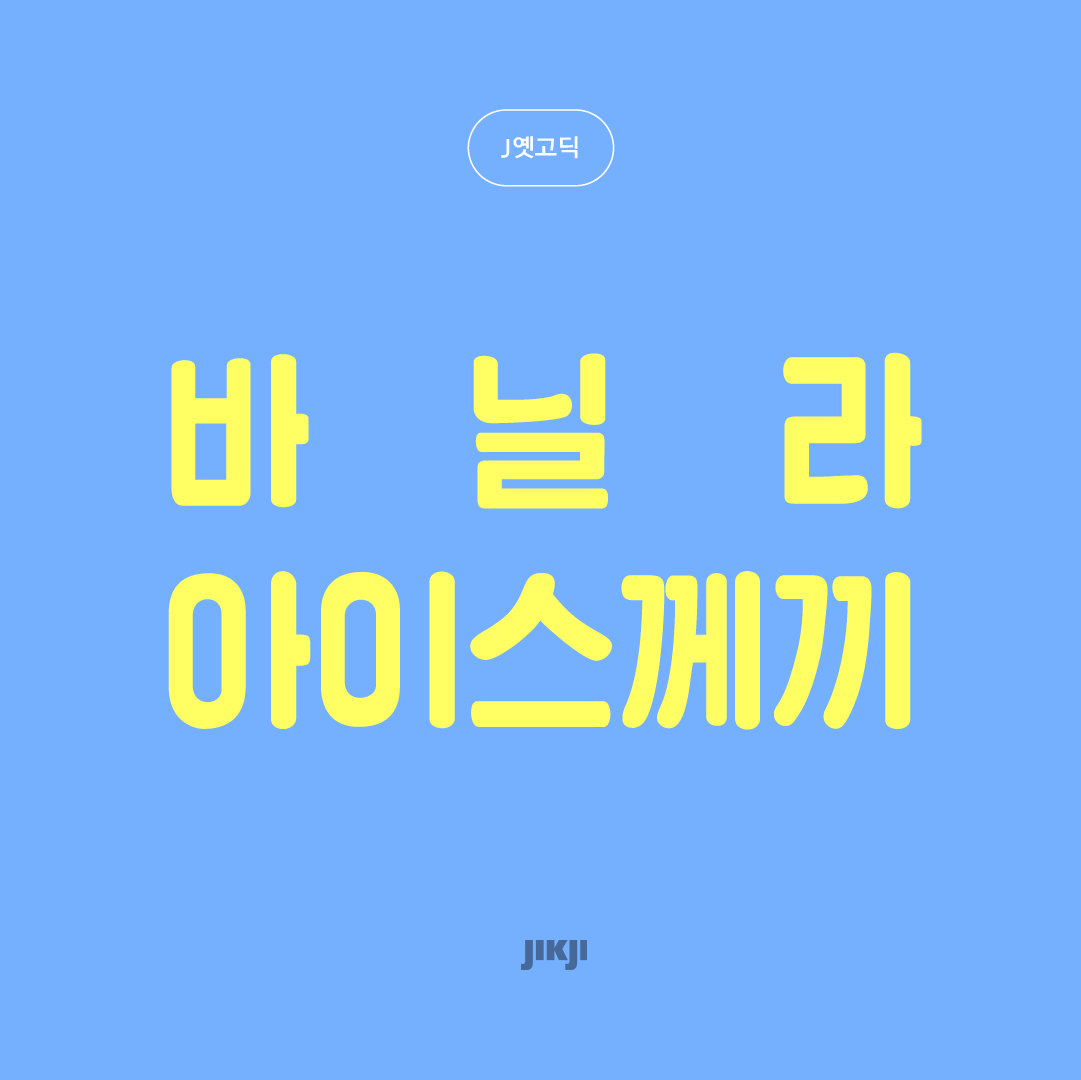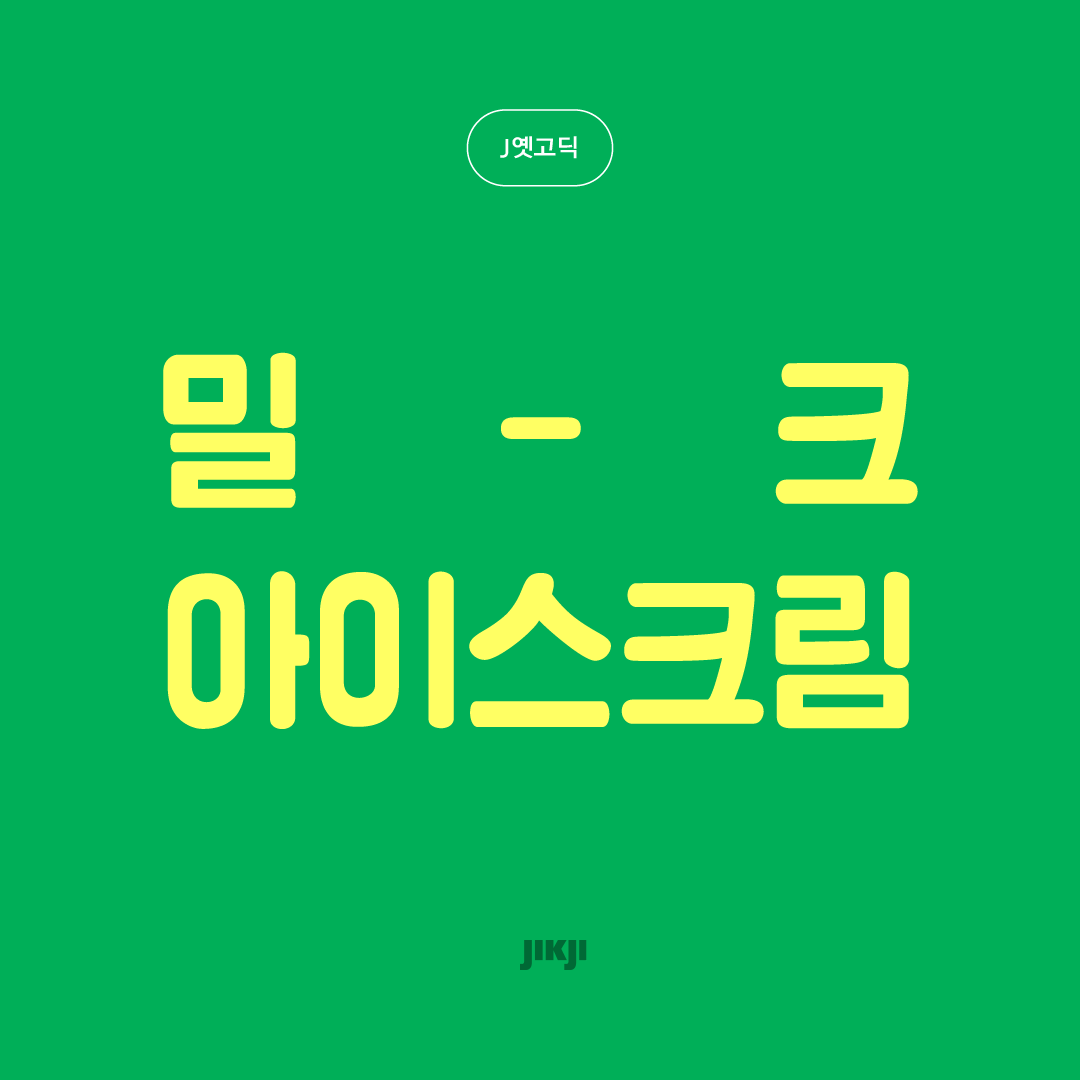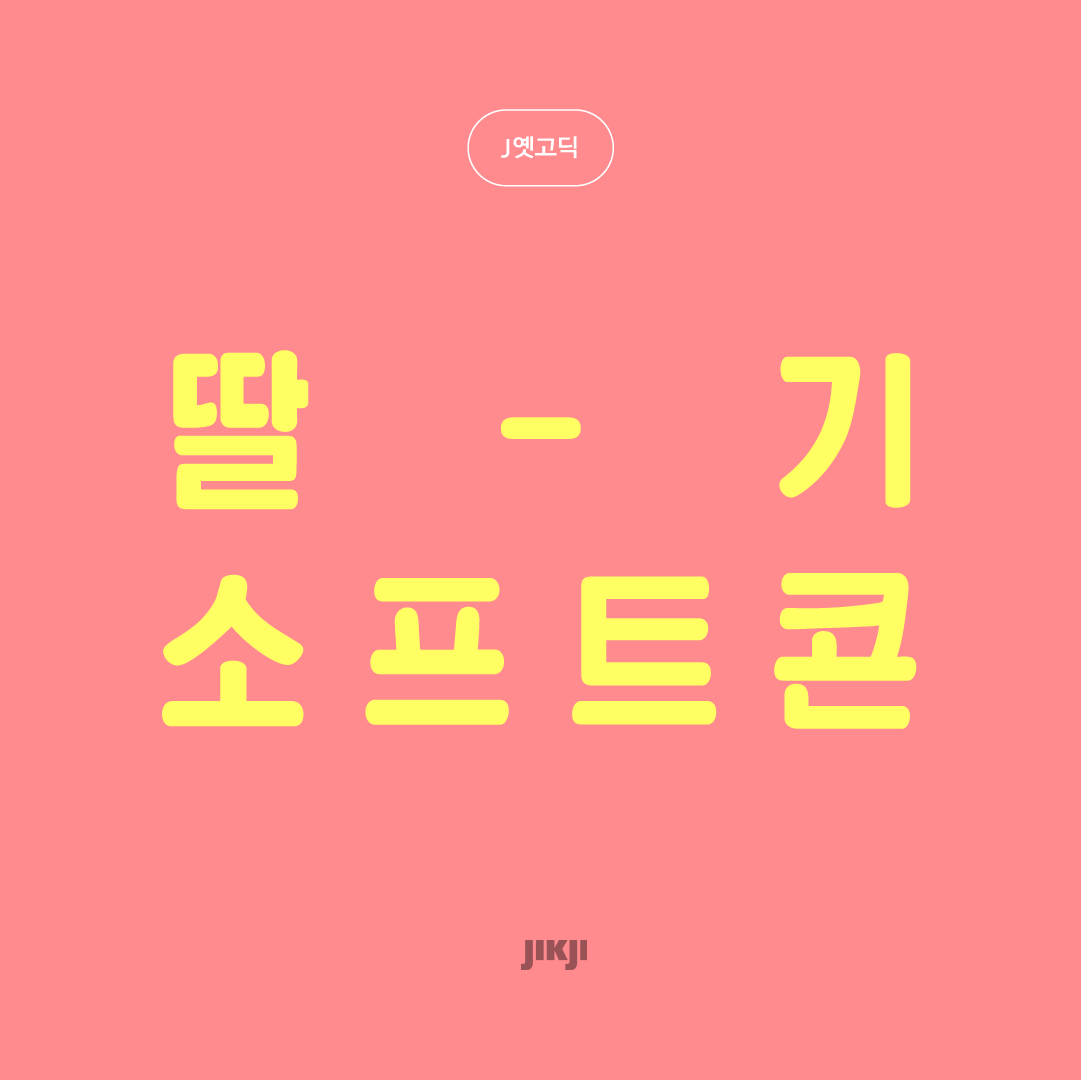
직지그래픽
다양한 컨셉으로 활용이 가능하고 독특한 디자인 요소가 많은 서체 시리즈. 개성있는 디테일로 시각적 재미를 더하고 풍부한 이야기를 담을 수 있는 서체이다.
오래된 간판이나 차트 글씨에서 볼 수 있었던 투박한 모양의 글씨체로 개발된 서체입니다.
J옛고딕은 직지소프트의 직지그래픽 폰트입니다. 출시일은 2019.01.01입니다. 1종으로 구성되어 있습니다.